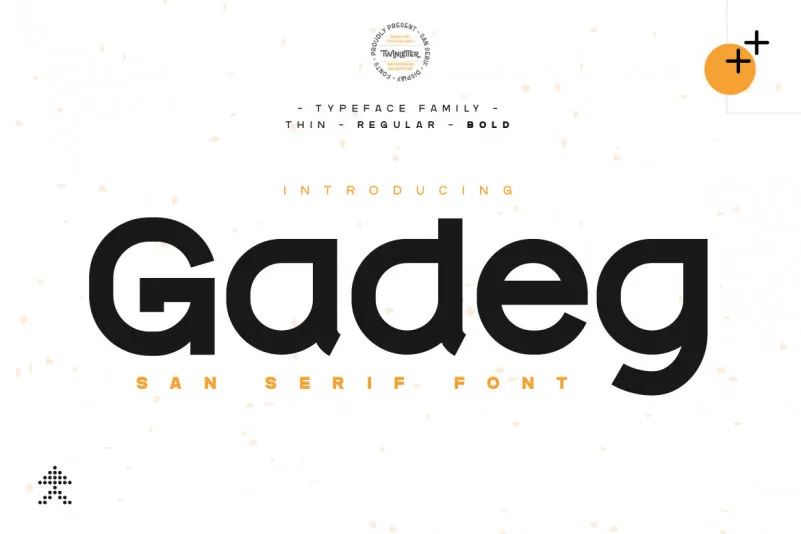
A “Gadeg Font” é uma tipografia sans-serif que abraça um estilo moderno e minimalista com uma simplicidade elegante. Inspirada na natureza, essa fonte adota formas únicas e especiais, criando uma impressão de transparência visual. A dupla de designers twinletter trouxe esta criação ao mundo da tipografia, oferecendo uma opção única para quem busca algo distintivo para suas produções digitais. Com seu design leve e moderno, a Gadeg Font torna-se ideal para uso em sites, apps móveis ou qualquer outro projeto que busque um toque de sofisticação sem perder o dinamismo necessário para comunicar efetivamente em tempos atuais. Uma fonte desta natureza ajuda a criar uma conexão emocional com seu público, seja ela uma empresa inovadora, um site criativo ou até mesmo o próximo app digital que transformará a maneira como as pessoas interagem e se comunham online.